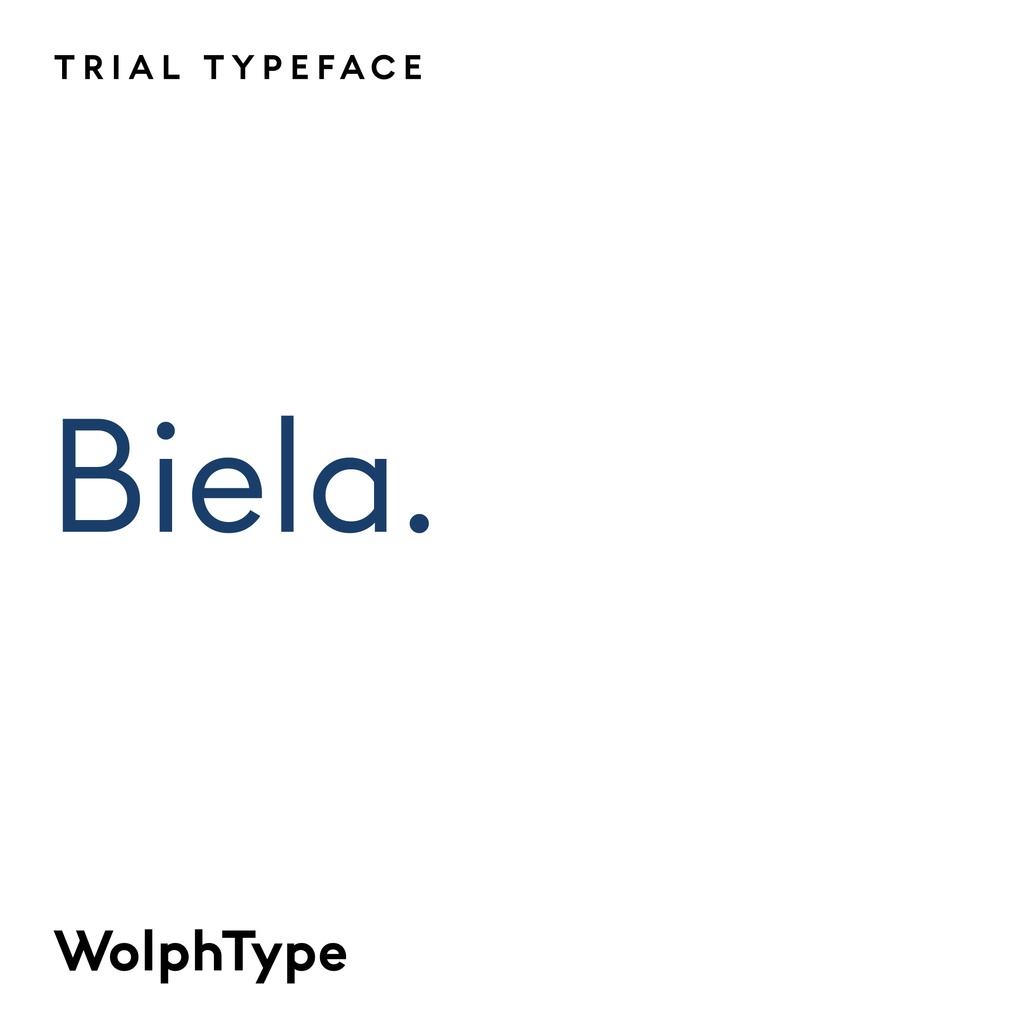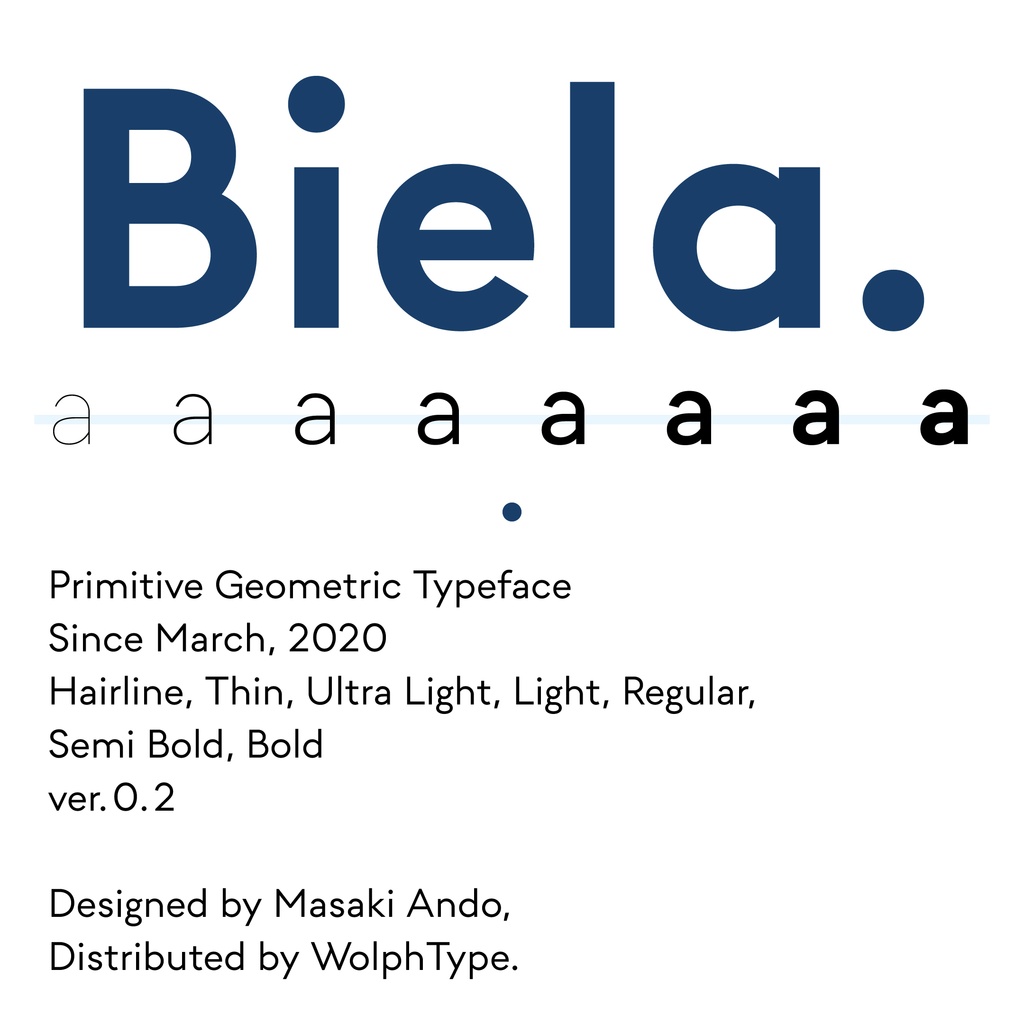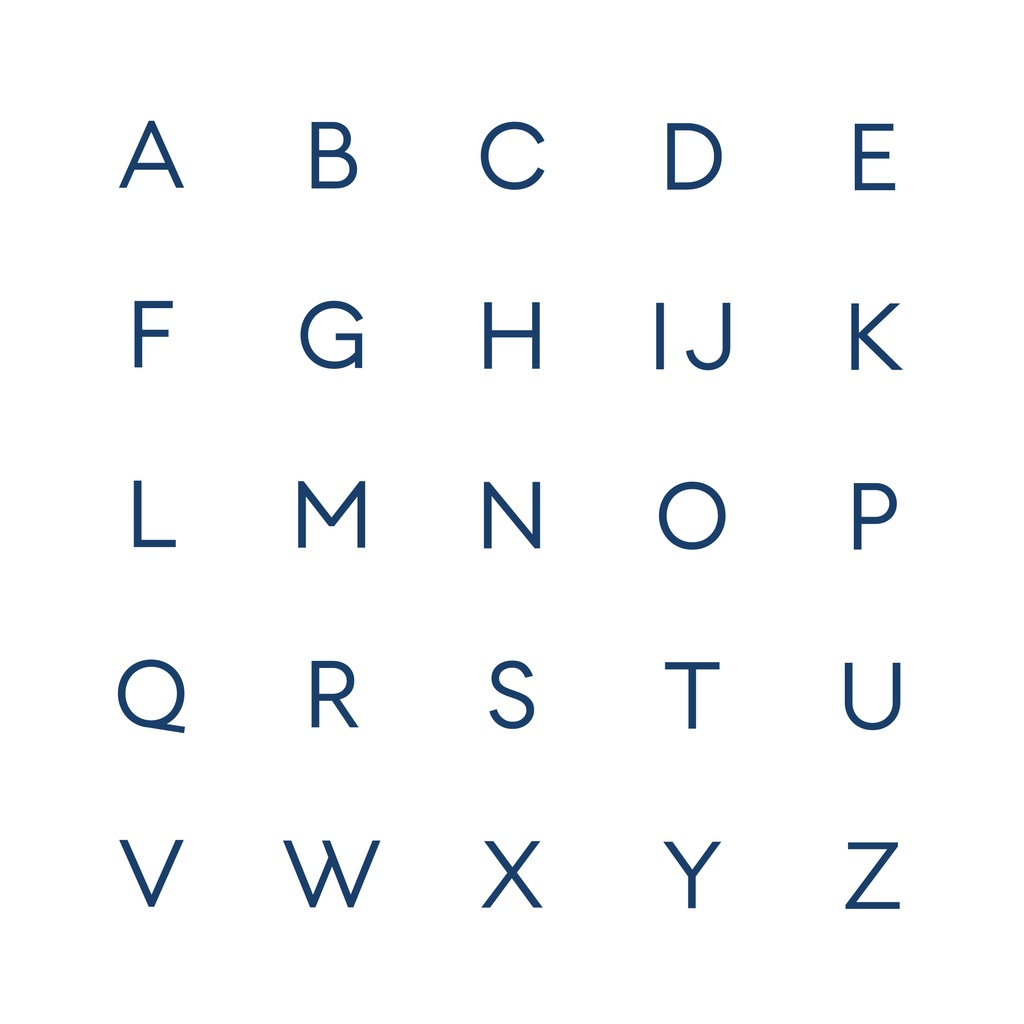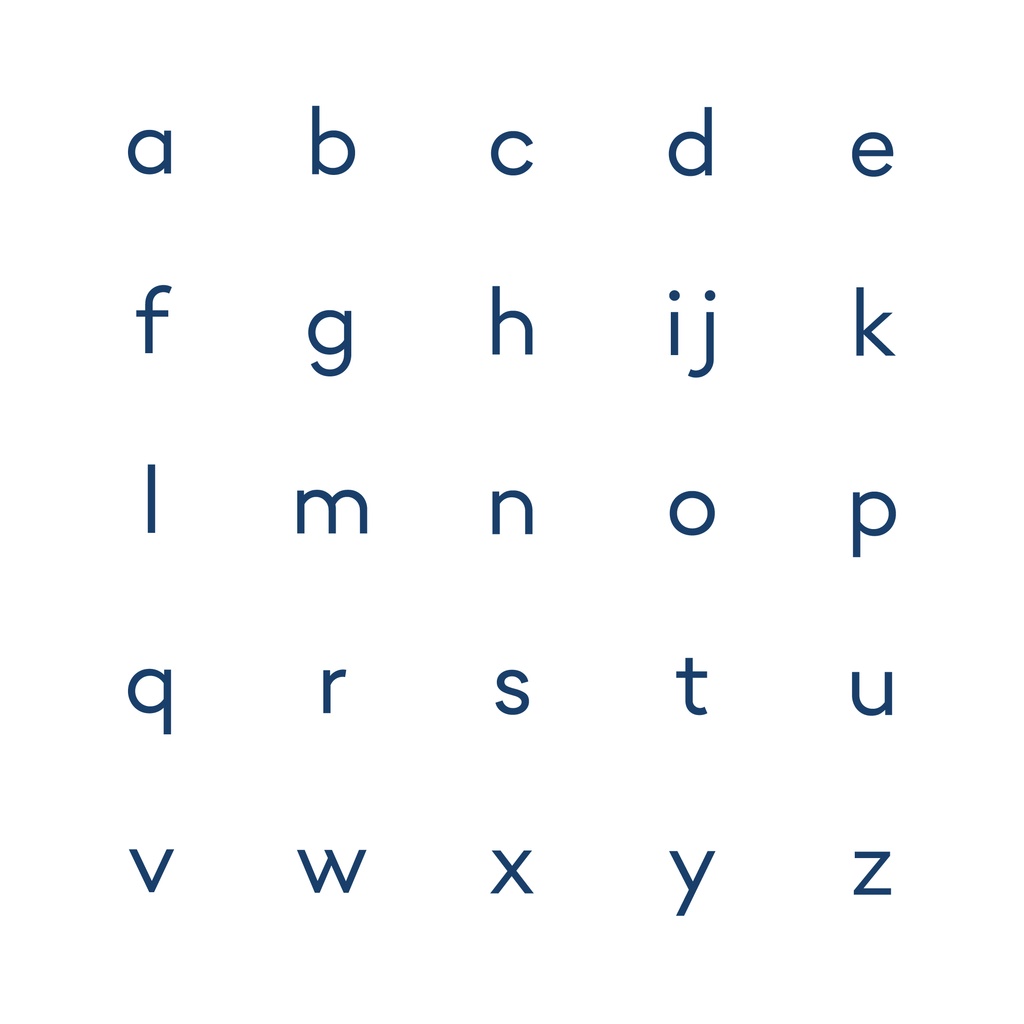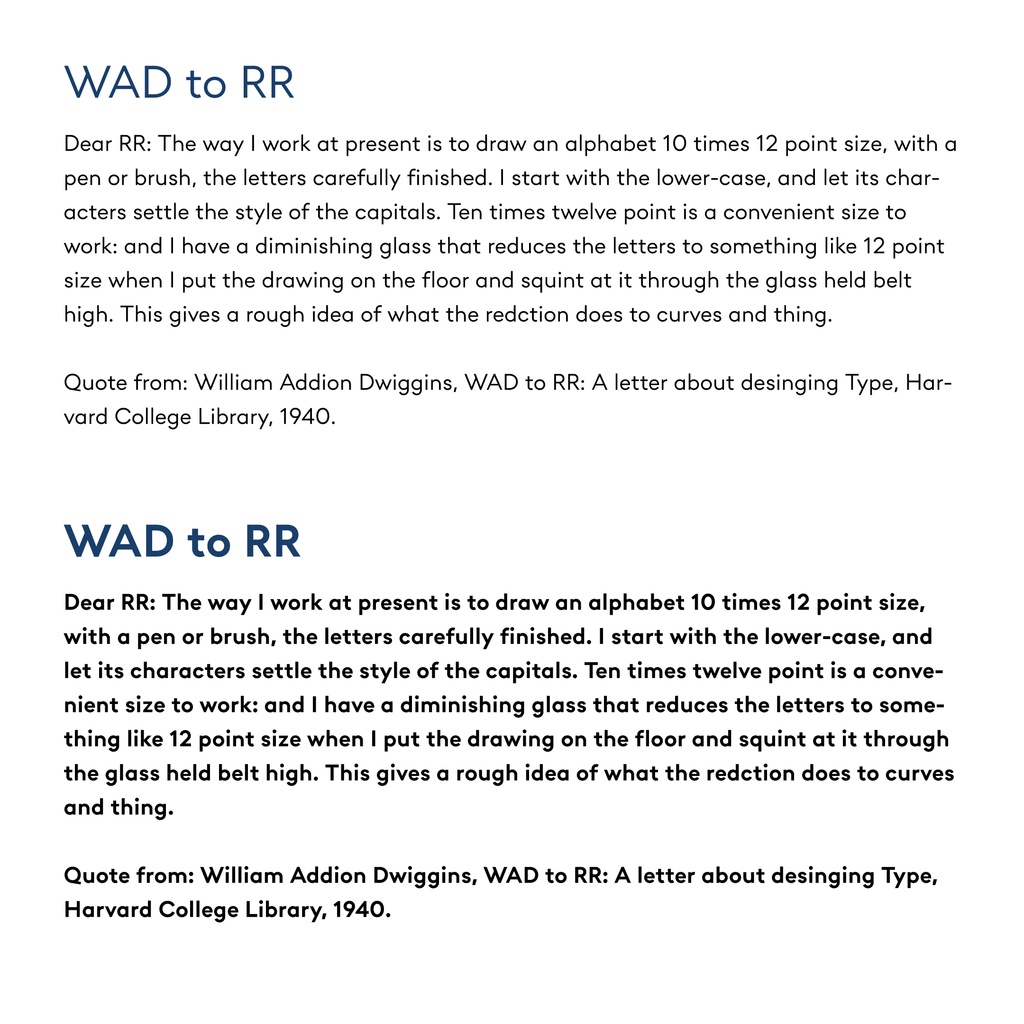
Biela Trial Fonts
ジオメトリックサンセリフ書体“Biela”のトライアルバージョンです。 見本帳の販売も行なっております。ぜひご覧ください。 https://wolphtype.booth.pm/items/3008887 非商用目的でのみ使用が可能です。必ず使用許諾書をお読みの上ご利用ください。 使用許諾書: https://www.dropbox.com/s/3hoxz4s2wuhuzyf/%E4%BD%BF%E7%94%A8%E8%A8%B1%E8%AB%BE%E6%9B%B8.pdf?dl=0 フォーマット: OpenType, バリアブルフォントのみTrueType 収録字種: 基本的な大文字、小文字、数字および一部記号のみに絞っています。